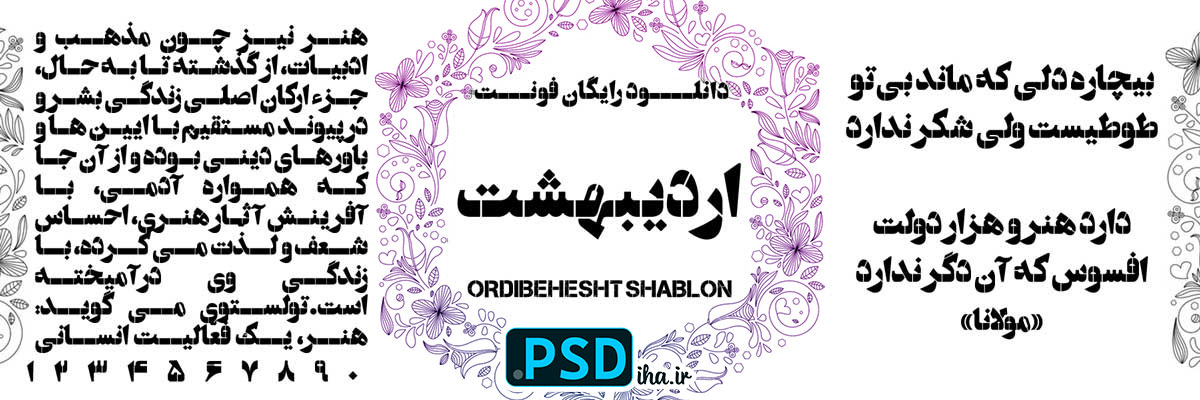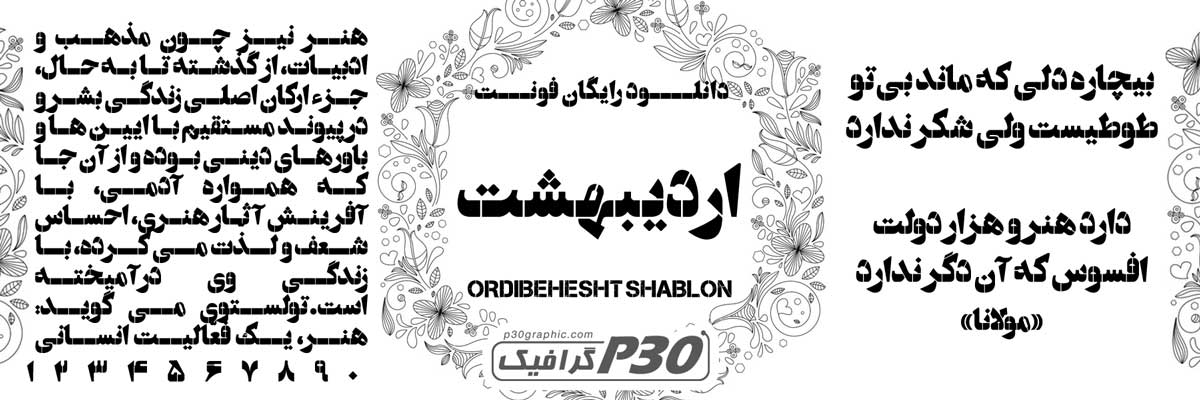
اگه از اونایی هستید که عاشق طرحهایی میشید که بوی مبارزه و ایثار میدن، فونت اردیبهشت شابلون رو حتماً امتحان کنید. من خودم تو پروژههای چاپی مرتبط با رویدادهای فرهنگی و انقلابی، از پلاکاردهای راهپیمایی تا تابلوهای مسجدی، بارها از این فونت استفاده کردم. هر بار، انگار کلمات زنده میشن و حس دفاع مقدس رو فوری منتقل میکنن. طراحیش، با خطوط محکم و شابلونوار، مستقیم از فضای تابلو نویسیهای خیابانی الهام گرفته – ایدهآل برای کارهای انقلابی با مضامین جنگ، شهادت و وحدت. تصور کنید شعار “استکبار ستیزی” یا “یاد شهدا” رو با این فونت روی دیوار بنویسید؛ مخاطبها فوری حس همدلی و قدرت میگیرن!
چرا فونت اردیبهشت شابلون برای کارهای انقلابی عالیه؟
این فونت رو نهادهای انقلابی، انجمنهای اسلامی، گروههای تبلیغاتی مساجد و ادارات عاشق شدن. تابلو نویسها و هنرآموزان هم ازش برای پلاکارد نویسی، دیوار نویسی و شابلون نویسی استفاده میکنن. خواناییش تو فاصلههای دور فوقالعادهست و تو چاپ یا رنگآمیزی دستی، لبهها تیز و مقاوم میمونن. با نرمافزارهایی مثل ایلاستریتور یا حتی ابزارهای ساده شابلون، بدون دردسر کار میکنه. یادمه یه پروژه برای هیئت مذهبی داشتم؛ با اردیبهشت شابلون، پلاکاردهای دفاع مقدس رو طراحی کردم. چاپشون روی پارچه انقدر محکم بود که تو راهپیمایی، باد هم تکونشون نداد. حالا دیگه تو هر رویدادی که بوی ایثار بده، اول سراغ این فونت میرم!
فونت اردیبهشت شابلون، با طراحی شابلونمحور، همه نیازهای تبلیغاتی رو پوشش میده. خطوط bold و صافش، برای تیترهای بزرگ مناسبه. انحناهای کمش، حس استحکام میده. با متنهای فارسی و عربی جور درمیاد. اگه میخواید پیامتون نه تنها دیده بشه، بلکه تو دلها بنشینه، این فونت ابزار دستتونه!
نکته عملی: برای شابلون نویسی، فونت رو تو اندازه بزرگ تست کنید و لبهها رو با برش لیزری چک کنید. من همیشه این کار رو میکنم. نتیجهش تمیز و ماندگاره.